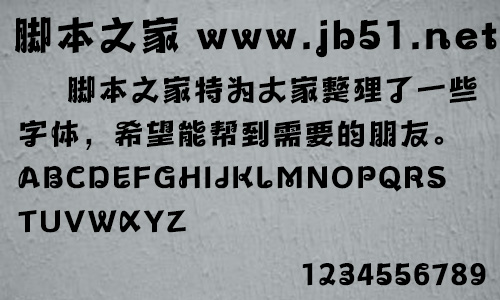
方正勁舞體簡Heavy字體是由方正字庫開發(fā)的一款中文字體,這款字體筆觸較為粗實,字體線條優(yōu)雅且美觀,適合應(yīng)用與藝術(shù)設(shè)計、平面宣傳設(shè)計、網(wǎng)頁設(shè)計、海報設(shè)計,書法字帖等領(lǐng)域。需要的朋友不妨前來本站下載。